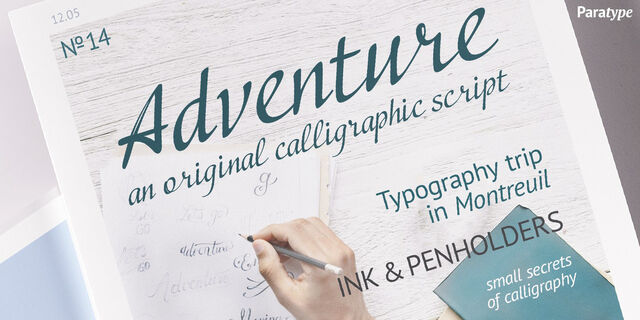
Оригинальный каллиграфический шрифт Adventure (Эдвенче) разработан дизайнером Натальей Васильевой в 2001 году в кириллическом комплекте знаков. В 2007 году были добавлены знаки западноевропейского комплекта, а в 2011 году — восточноевропейского. Шрифт предназначен для применения в рекламе и акциденции. В полной версии выпущен компанией ПараТайп в 2012 году.
динамичный, лихой, быстрый, красивый, оригинальный, свежий, бодрый, эмоциональный, здоровый, дружелюбный, летний, весенний, праздничный, новогодний, живой, прелестный, симпатичный, свободный, рождественский